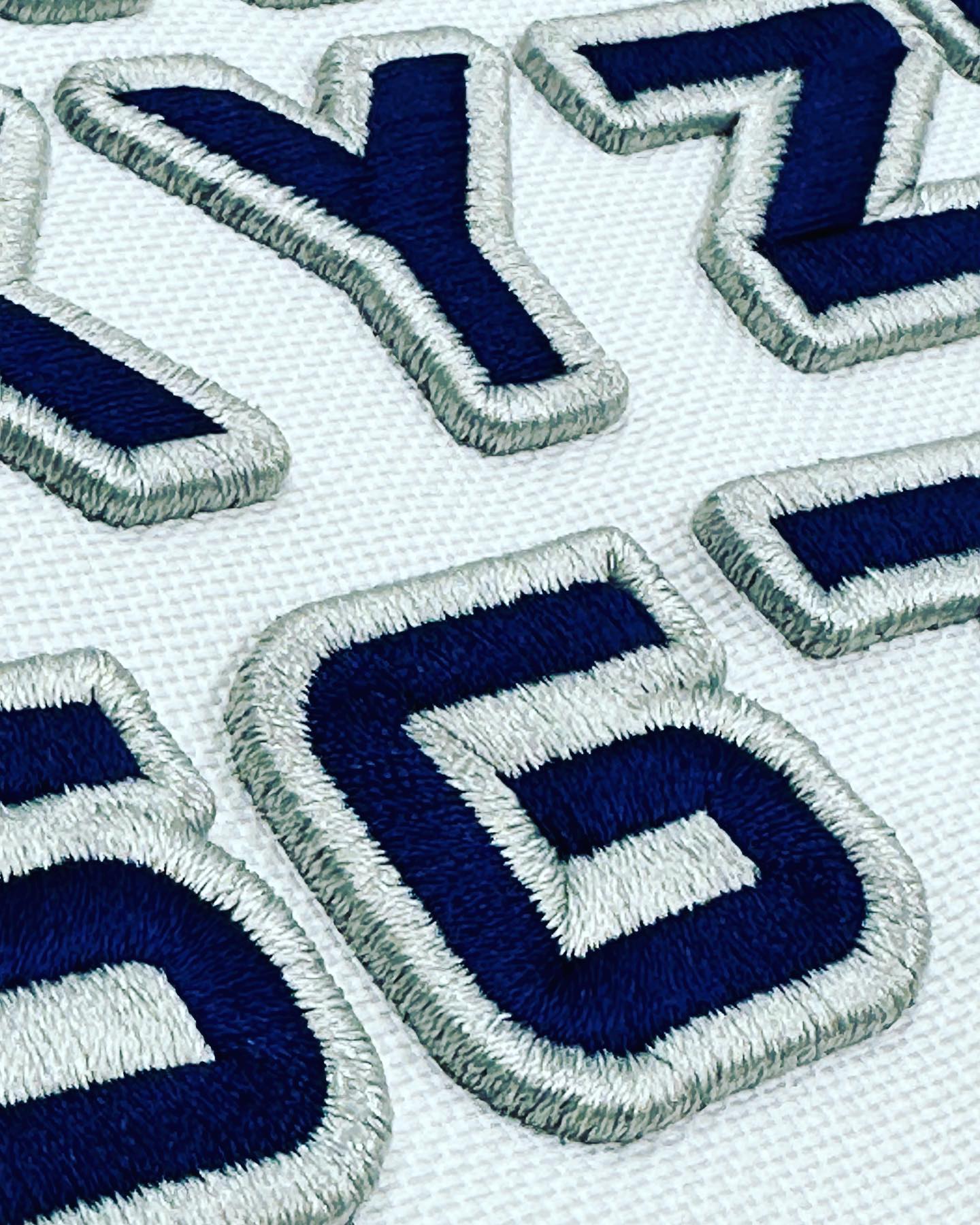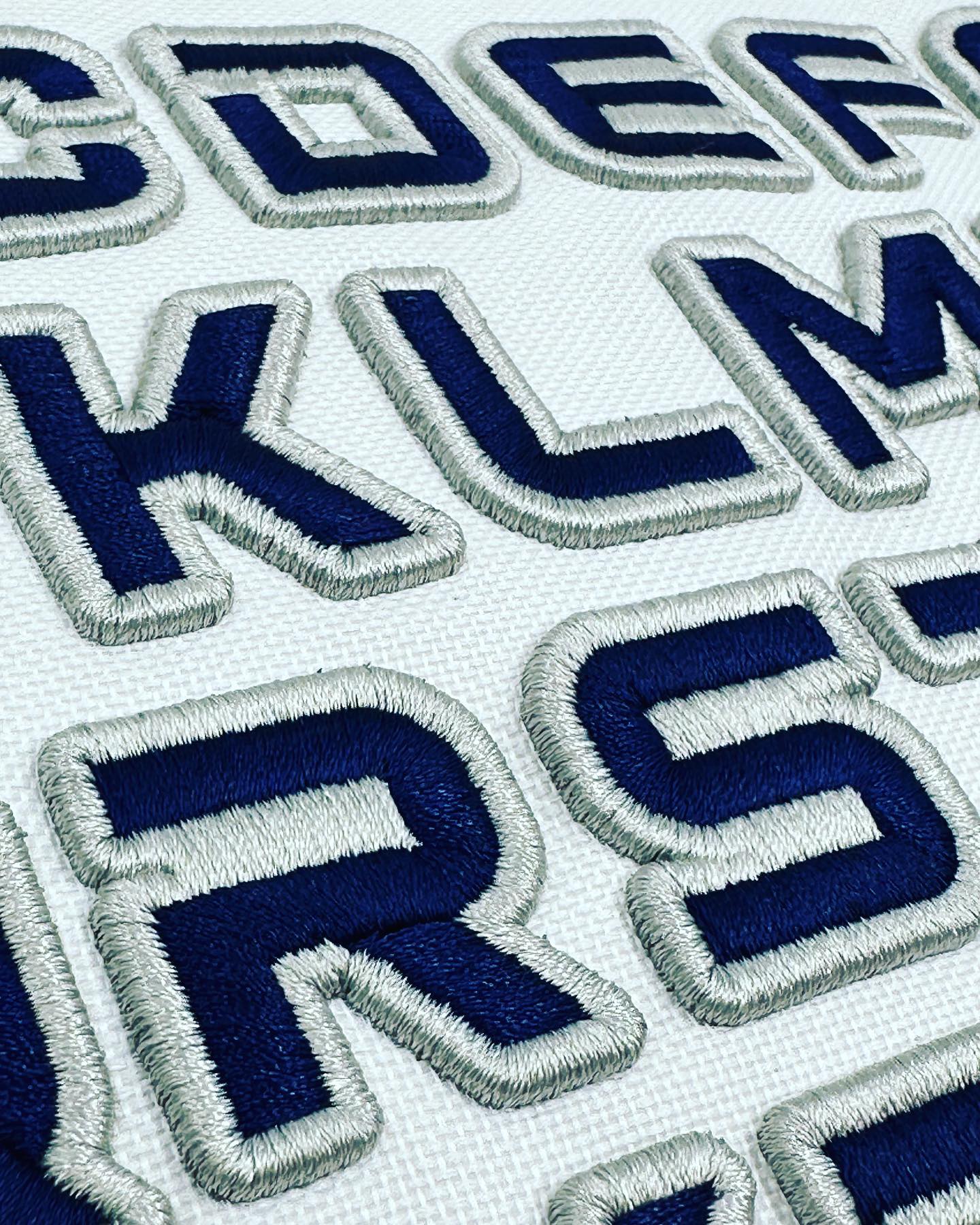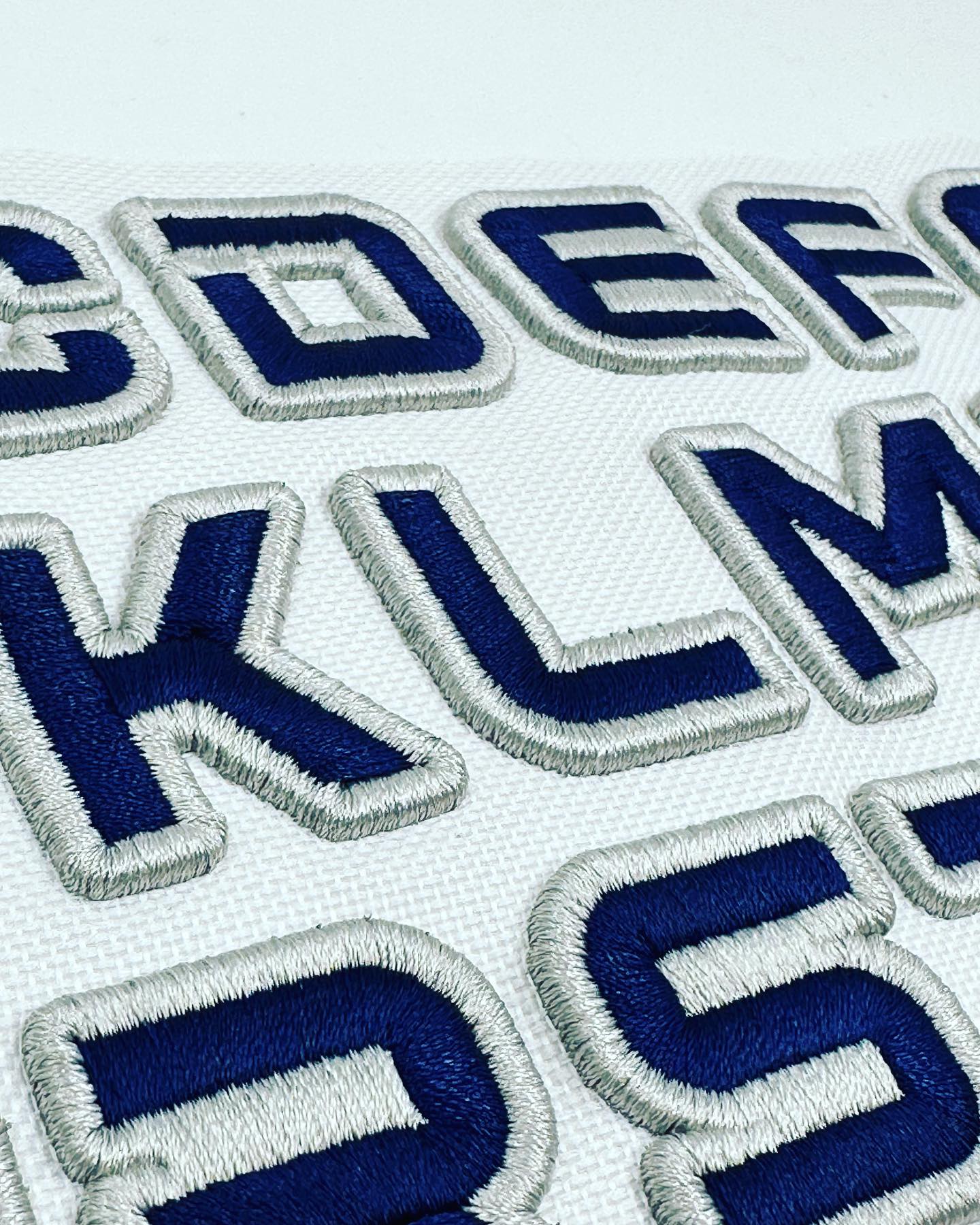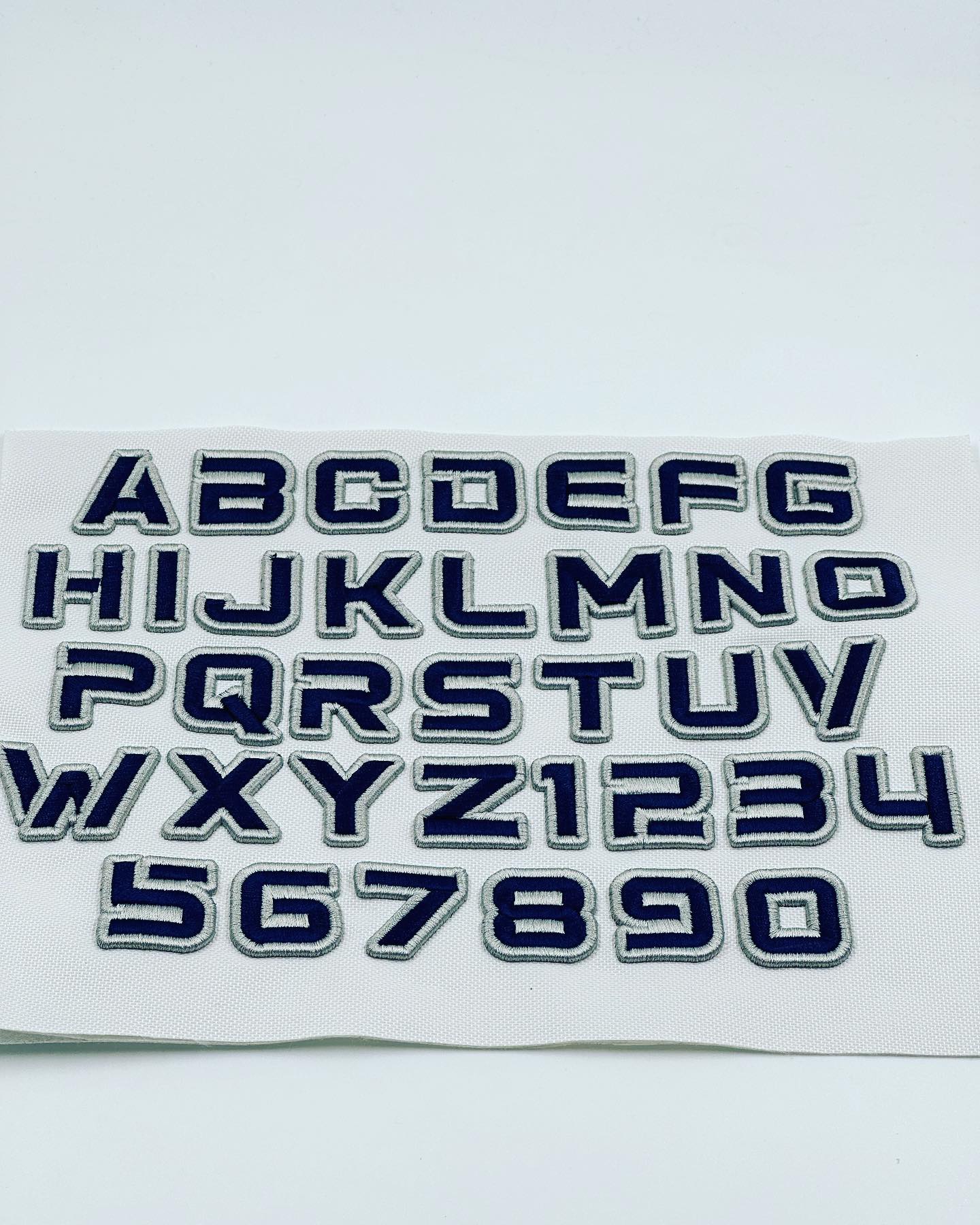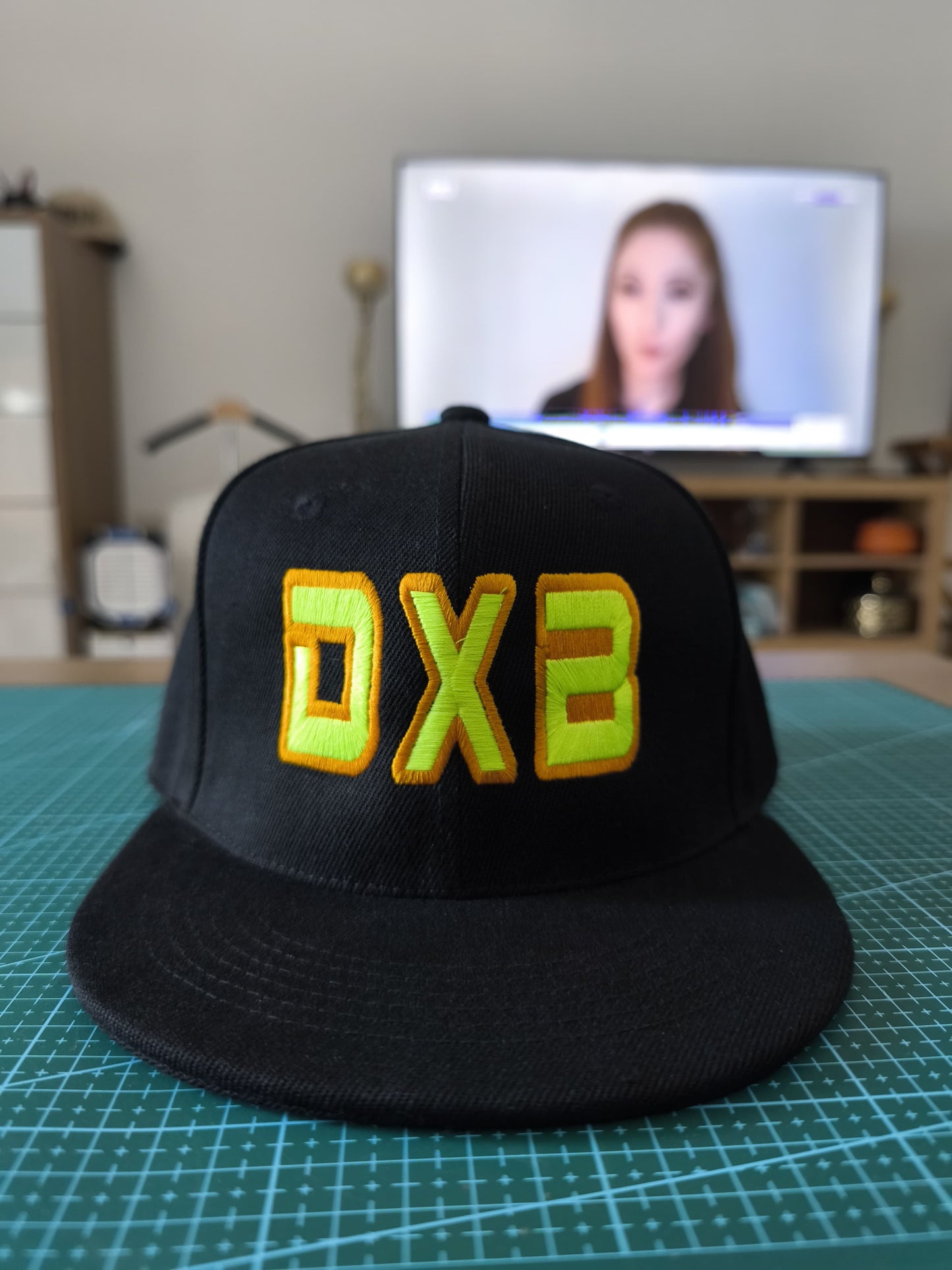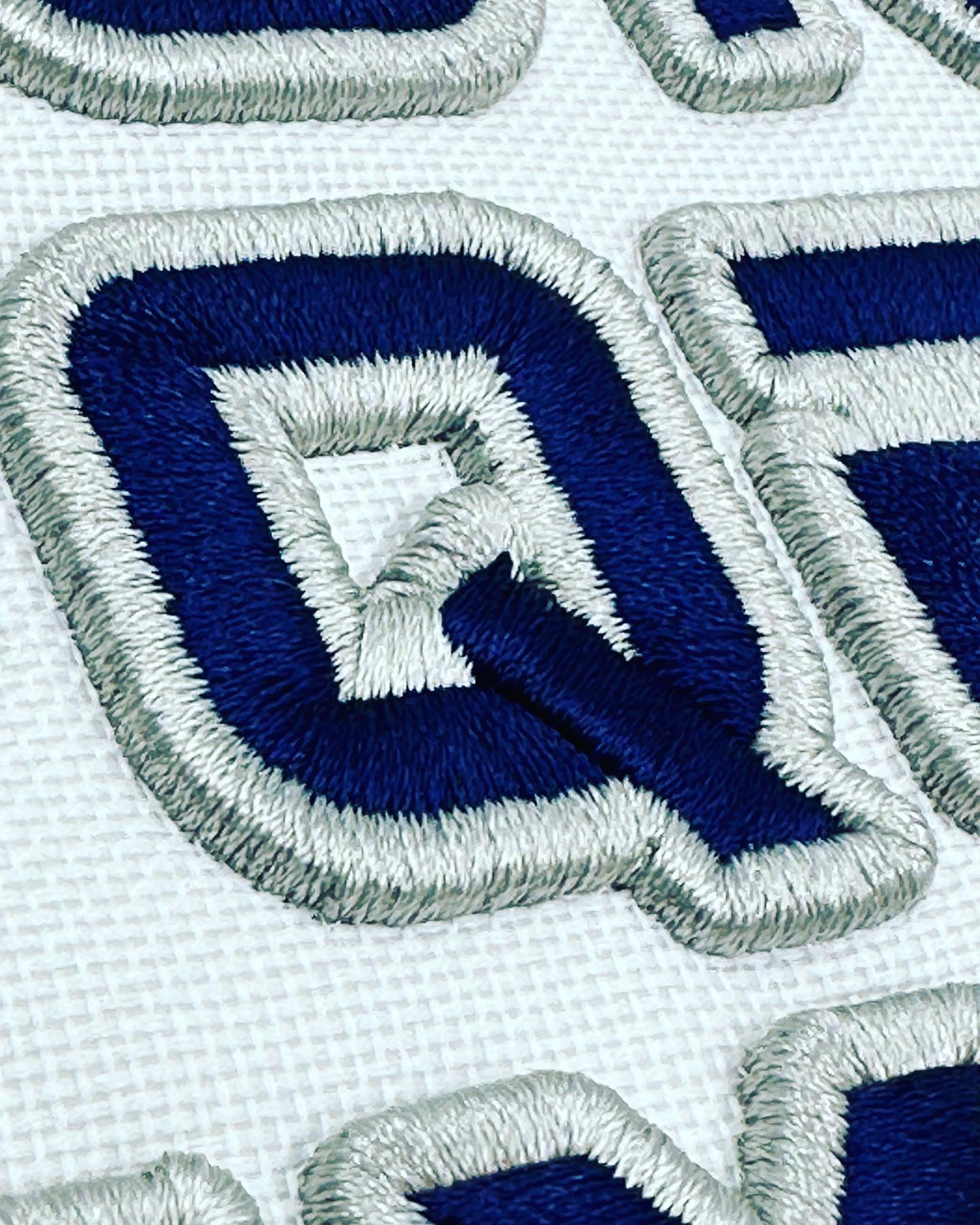
UnityRaised: مجموعة حروف التطريز ثلاثية الأبعاد
توحيد فريقك أو طاقمك أو قبيلتك مع UnityRaised — مجموعة حروف تطريز ديناميكية ثلاثية الأبعاد مصممة لتعزيز هوية المجموعة.
مثالية لجميع أنواع الفرق (الفرق الرياضية، أو فرق الأصدقاء المقربين، أو المنظمات المجتمعية)، تتميز هذه المجموعة حروف بارزة وجريئة مع خياطة مدعومة بالرغوة، مما يضمن ظهور اسم فريقك أو شعاره أو الأحرف الأولى من اسمه كعضو بأبعاد ملموسة وجذابة للنظر.
اختر من بين الخطوط الحادة أو الخطوط الأنيقة أو النصوص المرحة، وكلها قابلة للتخصيص بألوان خيوط نابضة بالحياة لتتناسب مع أجواء طاقمك.
🛡️ لماذا تحب الفرق هذه المجموعة:
• هوية المجموعة مكبرة: اصنع قبعات أو قمصان أو هوديس متطابقة بأحرف ثلاثية الأبعاد موحدة تصرخ فخر الفريق .
• صُممت لتدوم: تتمتع الخياطة المعززة بقدرة على تحمل أيام اللعب والمغامرات والغسيل الذي لا نهاية له.
• المرونة المخصصة: أضف أرقامًا أو رموزًا أو شعارات صغيرة إلى جانب الحروف لإضفاء لمسة شخصية.
من محاربي نهاية الأسبوع إلى الطواقم مدى الحياة، الوحدة المرفوعة يحول المعدات العادية إلى شارة انتماء. لأن الفرق تستحق أن تتألق معًا.